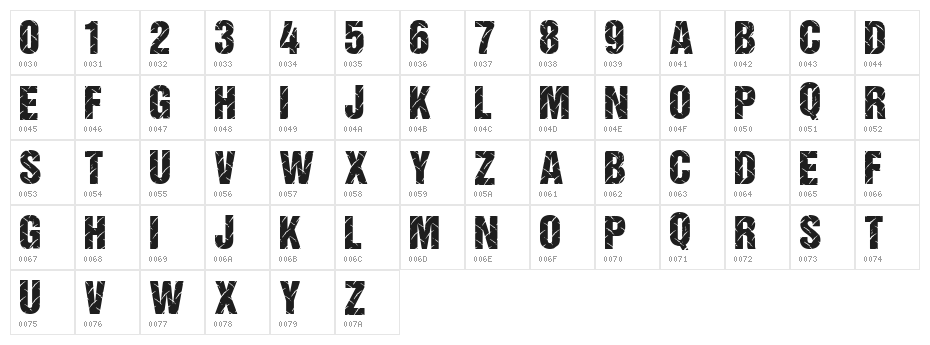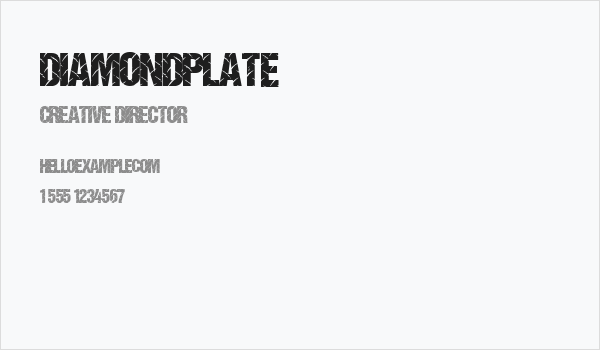
DiamondPlate Font
| Estilo geral | Modern, Industrial |
| Caso de uso | Logos, Posters, Signage |
| Projetos propostos | Ideal for use in industrial-themed designs, logos, posters, and signage that require a strong, impactful presence. |